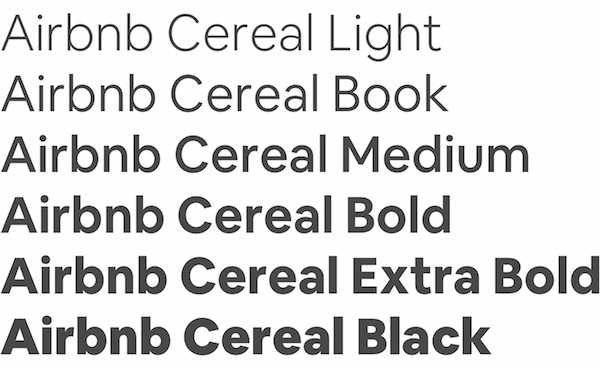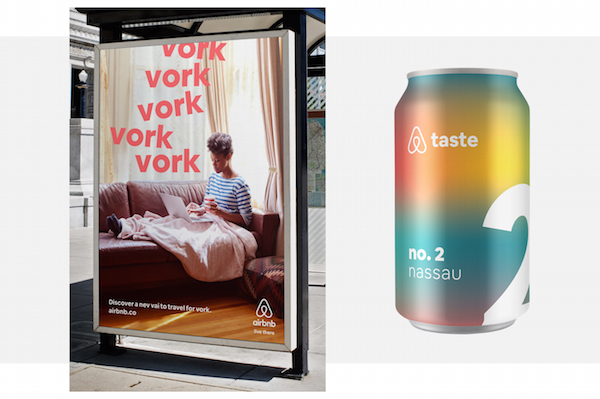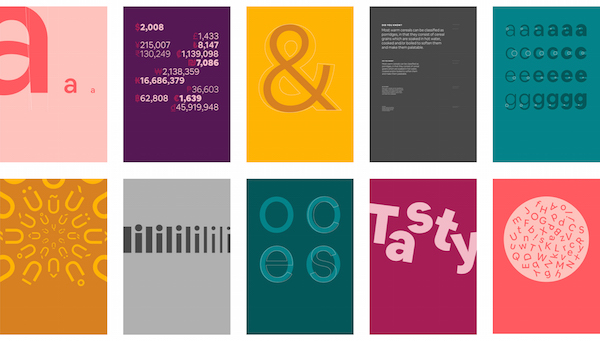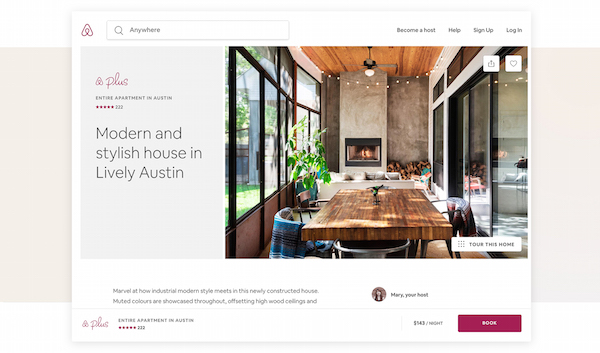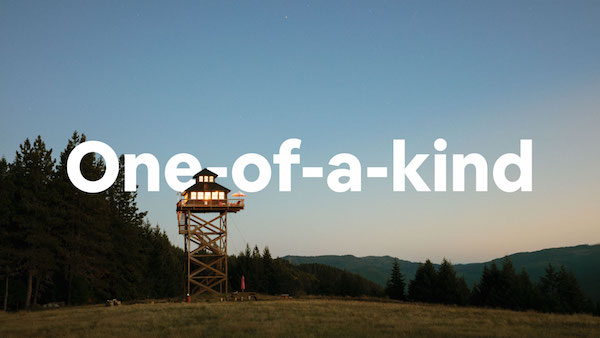
Las tendencias en el mercado han derivado en que marcas como Netflix y Coca-Cola hayan lanzado sus propias tipografías, las cuales, además de velar por el diseño propio un beneficio mercadológico y de egresos para la marca al no tener que estar pagando por los derechos de uso.
Ahora bien, a esta tendencia se sumado la marca Airbnb; la cual ha lanzado al mercado ‘Cereal’ su versátil tipografía pensada para ajustarse a sus parámetros de legibilidad de la marca en sus plataformas.
Cereal viene con gama colores y sombreado clásico en todas las tipografías; algo que le da ese toque clásico que nos encanta; y que está pensado para tener mayor presencia en las diferentes plataformas digitales y físicas de la marca.